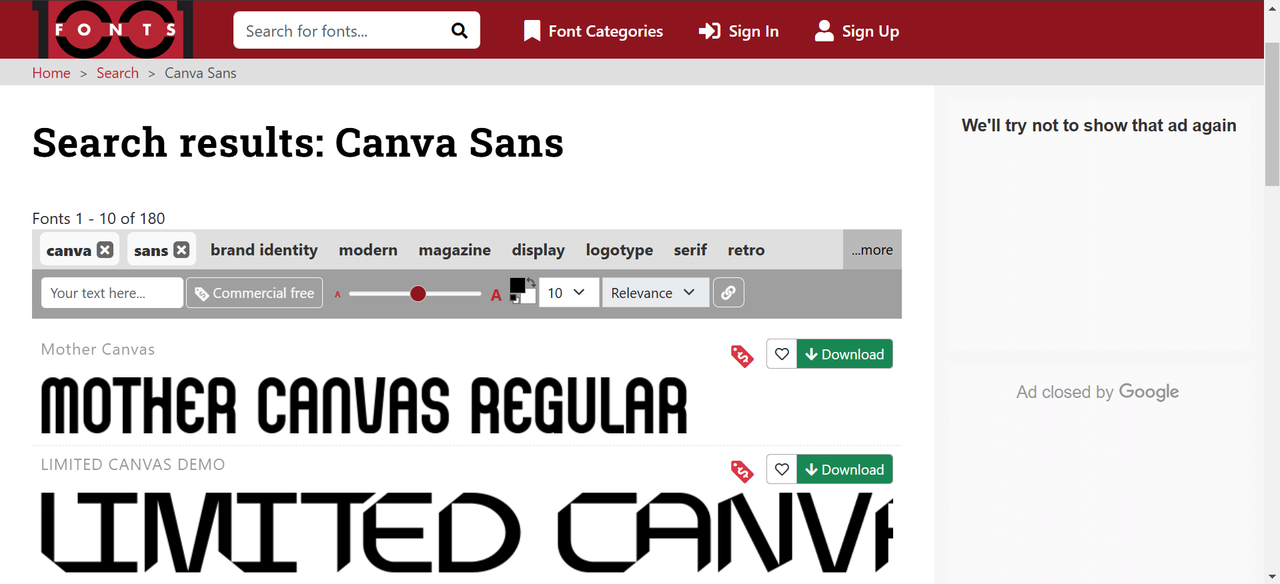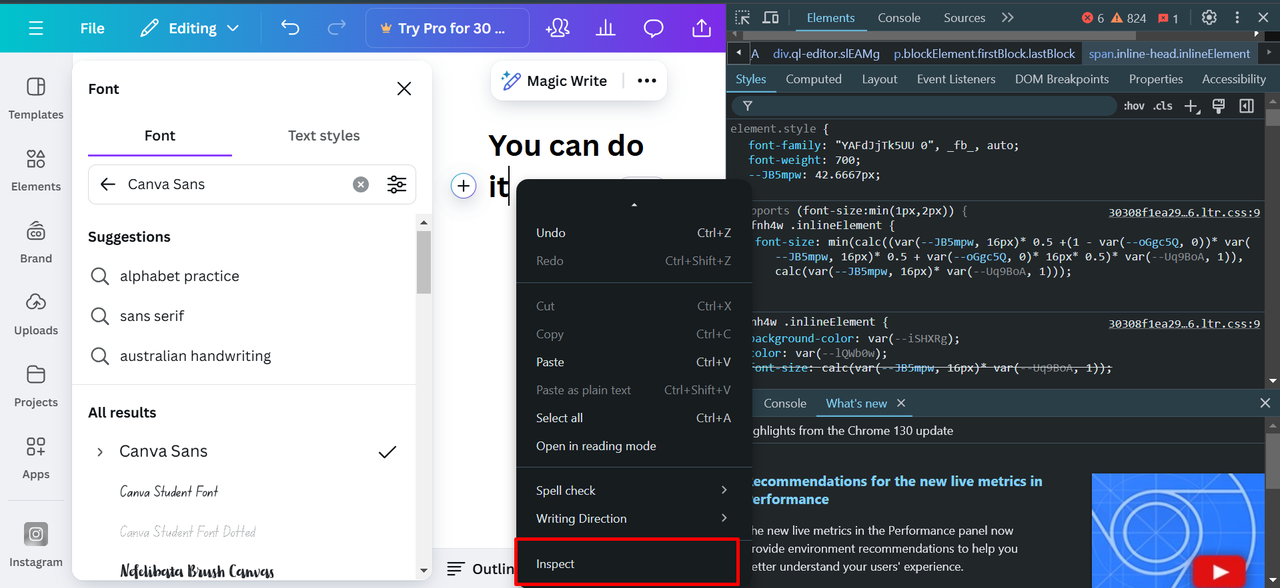
5 طرق سريعة لتنزيل Canva Sans Bold Font: عزز تصميماتك
استكشف طرقًا سهلة لتنزيل خط Canva Sans الغامق وجعل النص بارزًا على الدعوات والشعارات ورسومات الوسائط الاجتماعية. بدلاً من ذلك ، جرب محرر فيديو سطح المكتب CapCut واختر من بين مجموعة واسعة من أنماط الخطوط الجذابة.
كانفا بلا جريئة
يمنح خط Canva sans الغامق أي تصميم إحساسًا بالثقة والحداثة. يقترن بشكل جيد مع أنماط الخطوط الأخرى بالإضافة إلى أنواع مختلفة من العناصر. سواء تم استخدامه في الشعارات أو العناوين أو المواد الترويجية ، فإن هذا الخط يجلب الوضوح والأناقة إلى المقدمة.
ما هو خط Canva Sans
Canva Sans هو خط sans-serif نظيف وحديث تم إنشاؤه بواسطة Canva. يتميز بخطوط بسيطة وجريئة تجعل من السهل قراءتها ومتعددة الاستخدامات لمشاريع التصميم المختلفة. يعمل الخط جيدًا لكل من العناوين الكبيرة والنص الأصغر نظرًا لحوافه المستقيمة ونسبته. يعطي Canva Sans مظهرًا احترافيًا دون أن يكون صارمًا أو رسميًا في التصميم. إنه مثالي للشعارات ومنشورات الوسائط الاجتماعية التي توقف الإبهام لجذب انتباه الجمهور.
لماذا يحب المصممون خط Canva Sans الغامق للعلامة التجارية للمشروع
يعد خط Canva Sans الغامق خيارًا شائعًا بين المصممين ، وإليك سبب كونه المفضل:
1. شعارات العلامات التجارية الجريئة
بالنسبة للشعارات ، يوفر خط Canva Sans الغامق صورًا واضحة وملفتة للنظر. تجعل خطوطها القوية الشعارات يمكن التعرف عليها على الفور وتخلق انطباعًا دائمًا مع الحفاظ على البساطة والأناقة.
1. عناوين جذابة
تحتاج العناوين الرئيسية إلى جذب الانتباه ، و Canva Sans bold يفعل ذلك بالضبط. تضمن جرأتها أن تجذب الرسالة عين المشاهد دون التغلب على التصميم.
1. إشراك مقدمات العرض
يعد بدء عرض تقديمي ببيان جريء أمرًا سهلاً مع Canva Sans Bold. يضمن تصميمه النظيف والجريء أن الشرائح التمهيدية لها تأثير قوي وجذاب يحافظ على تركيز الجمهور على الرسالة.
1. دعوات حدث أنيقة
بالنسبة لدعوات المناسبات ، يضيف خط Canva Sans الغامق لمسة عصرية وأنيقة. تمنح الأناقة البسيطة أي دعوة لإطلالة نصية مذهلة تناسب المناسبات غير الرسمية والرسمية.
1. تعزيز الترقيات المنتج
يعمل خط Canva Sans الغامق على العجائب لترويج المنتجات. يساعد المظهر الجريء للخط على أن تكون المواد الترويجية للمنتج الرئيسي أكثر جذبًا للانتباه ولا تنسى.
1. هل يمكنني تخصيص خط Canva Sans الغامق في تصميماتي ؟
نعم ، يمكنك تخصيص خط Canva Sans الغامق في تصميماتك عن طريق ضبط حجمه ولونه وتباعده ليناسب احتياجات مشروعك. تمكّنك هذه المرونة من تحسين التأثير البصري مع ضمان الاتساق مع نمط علامتك التجارية أو أهداف التصميم. علاوة على ذلك ، لتحسين مقاطع الفيديو بخط غامق ، استخدم محرر فيديو سطح المكتب CapCut. تتيح لك مكتبة الخطوط الواسعة اختيار ما يناسبك.